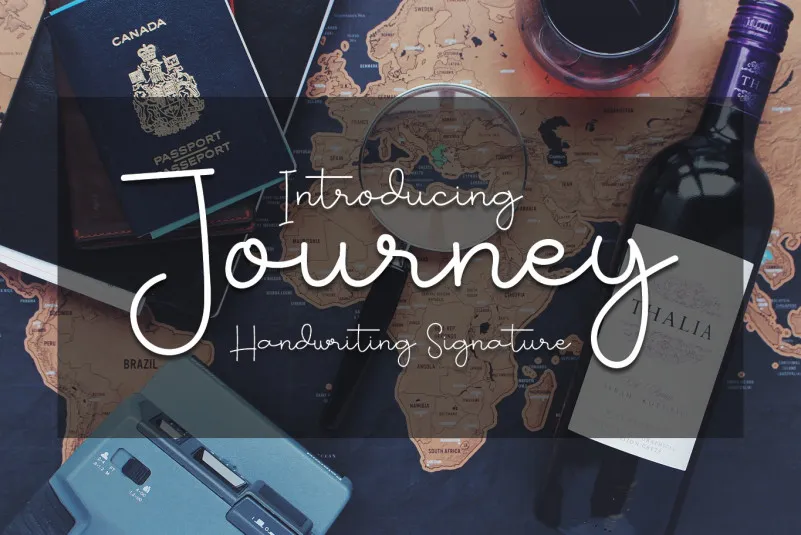
Journey Font – Download Grátis
A Journey Font é uma elegante e leve fonte escrita à mão com um toque único que desperta grande impacto visual. Esta fonte esbanja charme e luxúria, fazendo do seu uso uma escolha refinada para qualquer projeto gráfico a ser iniciado. Seja um design de site, cartão de visita ou até mesmo um documento pessoal, Journey Font trará uma atmosfera encantadora às criações que você desejar. Perfeita tanto para projetos criativos quanto para aquelas necessidades mais formais, ela certamente é a escolha ideal para adicionar o toque final que sua arte precisa.